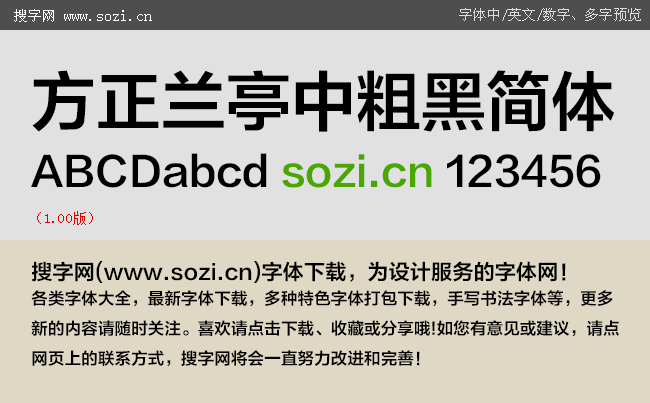
方正蘭亭中粗黑簡(jiǎn)體
搜字網(wǎng)提供一款方正蘭亭中粗黑簡(jiǎn)體字體下載,方正蘭亭中粗黑簡(jiǎn)體是一款黑體字體,該字體端正大方,筆鋒粗曠,整體風(fēng)格出色,適用于廣告設(shè)計(jì)、名片設(shè)計(jì)、包裝印刷、產(chǎn)品設(shè)計(jì)等應(yīng)用。